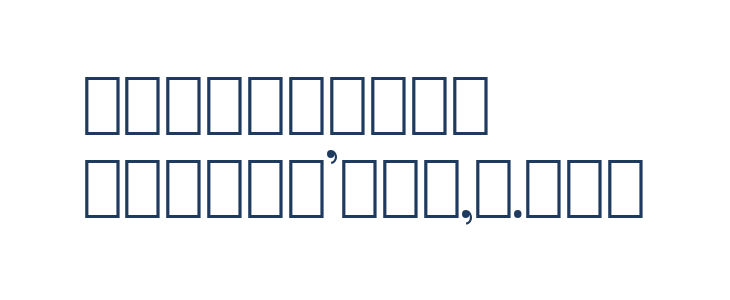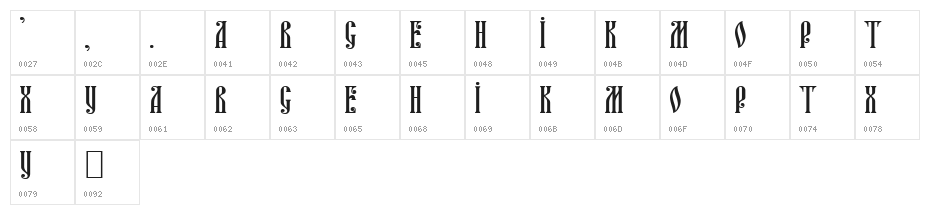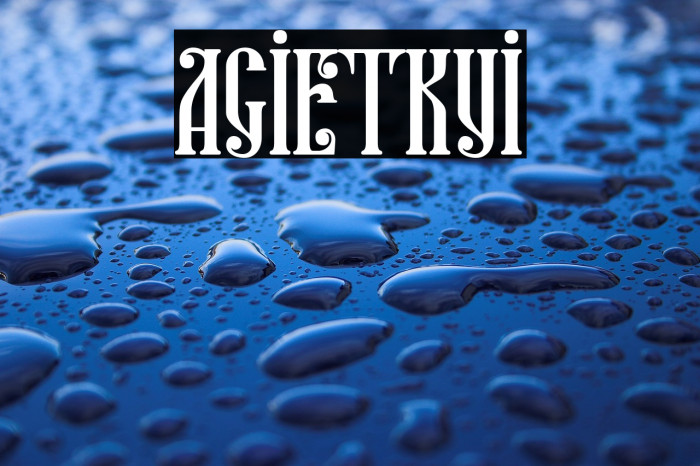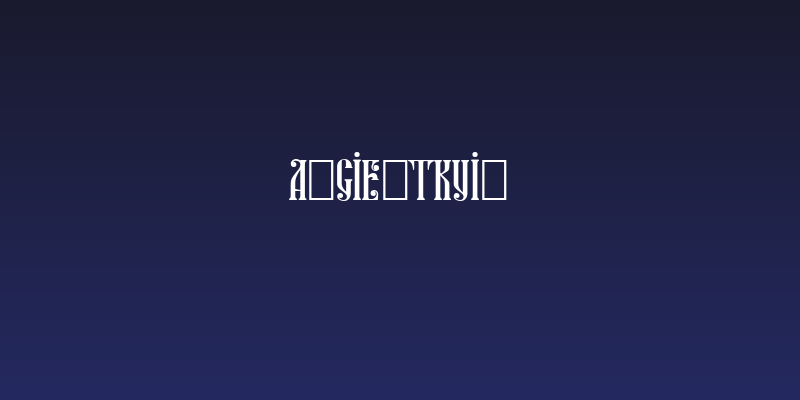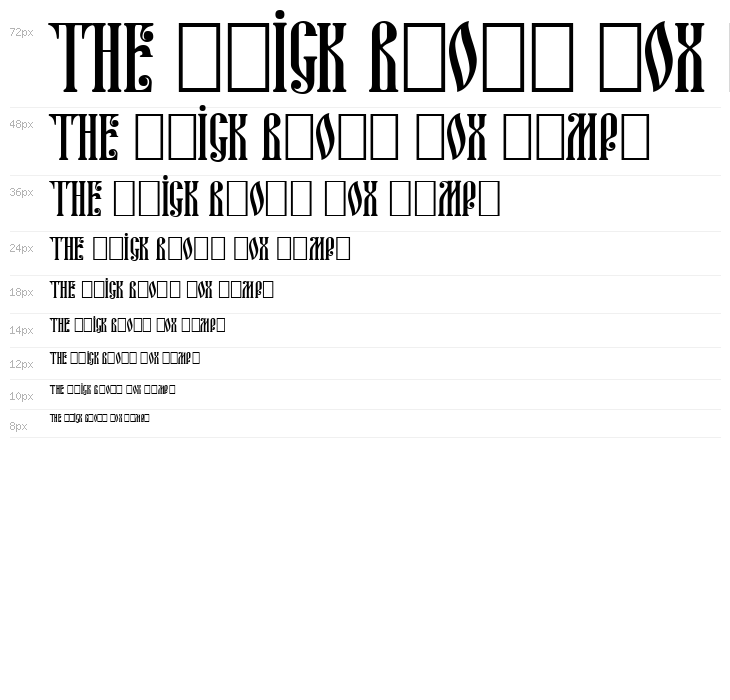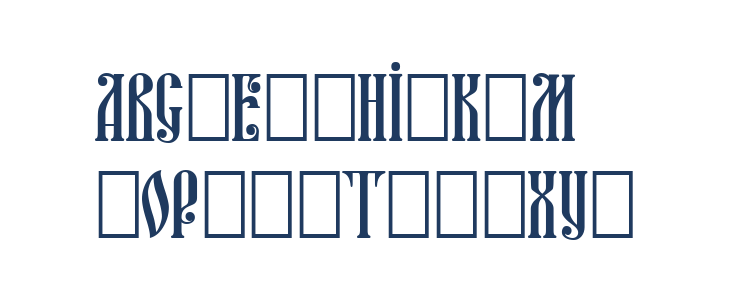
AncientKyiv Font
✎ Curly
| Caso d'uso | Headlines, Logos, Decorative text |
| Progetti proposti | Ideal for historical-themed designs, invitations, posters, and branding that requires a touch of elegance and sophistication. |